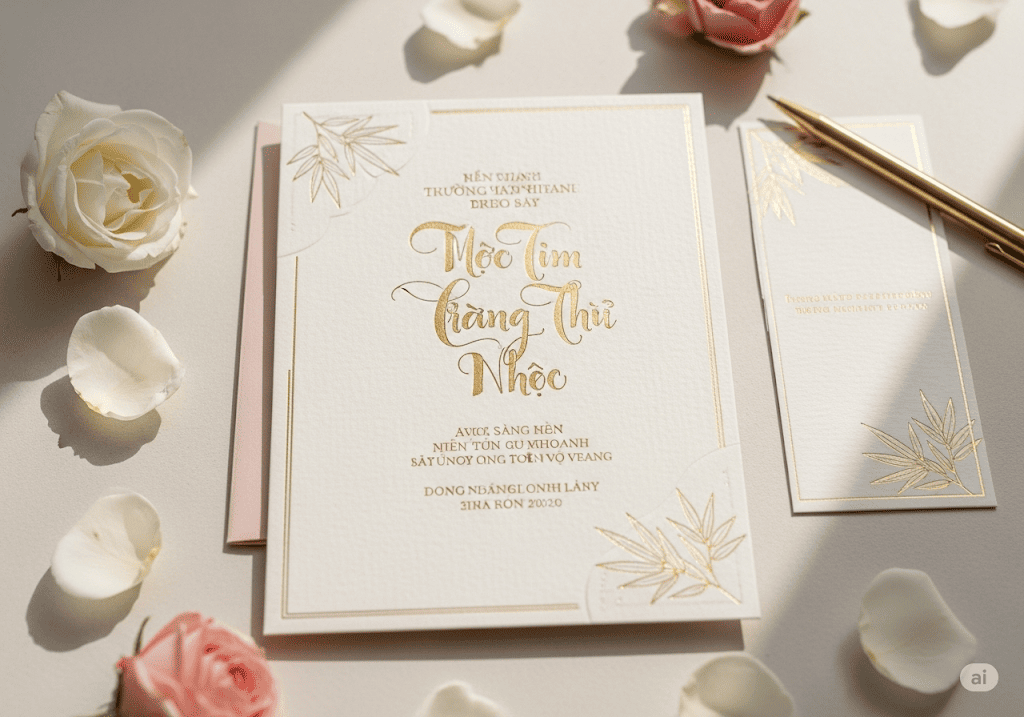
Tìm kiếm một font chữ thư pháp việt hóa vừa đẹp vừa không lỗi hiển thị có thể khiến bạn mất khá nhiều thời gian. Để giúp bạn, chúng tôi đã tuyển chọn và kiểm tra kỹ lưỡng danh sách hơn 20 bộ font miễn phí, sẵn sàng để bạn tải về và thổi hồn văn hóa Việt vào các thiết kế của mình.
Chắc hẳn bạn đã từng khó chịu khi tải về một font thư pháp ấn tượng, nhưng khi gõ tiếng Việt lại bị vỡ ký tự ‘đ’, ‘ă’ hay mất dấu thanh. Đây là vấn đề phổ biến nhất, làm ảnh hưởng trực tiếp đến chất lượng của các ấn phẩm quan trọng như thiệp chúc Tết, bìa sách hay bao bì sản phẩm.
Bài viết này không chỉ là một danh sách để tải về. Chúng tôi sẽ đi sâu vào cách nhận biết một font đã được Việt hóa chuẩn, hướng dẫn cài đặt nhanh chóng và chia sẻ các mẹo phối hợp chuyên nghiệp để tạo ra những tác phẩm thực sự có hồn và đẳng cấp.
Trước khi khám phá bộ sưu tập, hãy cùng tìm hiểu nền tảng cốt lõi: font thư pháp Việt hóa thực chất là gì và tại sao nó lại là yếu tố không thể thiếu trong thiết kế hiện đại.
Font chữ thư pháp Việt hóa là gì và tại sao lại được ưa chuộng?
Tại sao font chữ thư pháp Việt hóa lại quan trọng trong thiết kế?
Về cơ bản, font thư pháp là gì? Đây là một bộ ký tự số hóa mô phỏng nét bút lông uyển chuyển của nghệ thuật thư pháp truyền thống, nhưng đã được tinh chỉnh kỹ thuật để hiển thị đầy đủ và chính xác hệ thống dấu câu phức tạp của tiếng Việt. Việc “Việt hóa” này chính là yếu tố cốt lõi tạo nên giá trị sử dụng thực tế của chúng.
Sử dụng chữ thư pháp tiếng việt không chỉ là một lựa chọn thẩm mỹ, mà còn mang lại chiều sâu văn hóa và cảm xúc cho thiết kế. Ví dụ, một tấm thiệp chúc Tết, bìa sách về lịch sử, hay bao bì sản phẩm truyền thống sẽ ngay lập tức trở nên có hồn và trang trọng hơn. Đây là cách nhanh nhất để truyền tải giá trị cội nguồn trong bối cảnh typography việt nam hiện đại. Tuy nhiên, sai lầm phổ biến nhất mà nhiều người mới mắc phải là sử dụng các font chưa được Việt hóa hoàn chỉnh, dẫn đến lỗi hiển thị các ký tự như ‘đ’, ‘ă’, ‘ư’ hoặc các dấu thanh.
Để tránh lãng phí thời gian và đảm bảo chất lượng thiết kế, hãy luôn kiểm tra font trước khi sử dụng bằng quy trình đơn giản sau:
- Gõ một câu tiếng Việt đầy đủ dấu: “Mừng xuân sang, chúc vạn sự thành công tốt đẹp.”
- Nếu tất cả ký tự và dấu câu hiển thị mượt mà, không bị vỡ hay biến thành ô vuông, font đó đã sẵn sàng để sử dụng.
Hiểu rõ ý nghĩa font thư pháp và tầm quan trọng của việc Việt hóa sẽ giúp bạn lựa chọn công cụ phù hợp, tạo nền tảng vững chắc cho các tác phẩm của mình. Giờ thì hãy cùng khám phá danh sách các font đẹp nhất đã được chúng tôi tuyển chọn kỹ lưỡng ở phần tiếp theo.
Đâu là những font chữ thư pháp Việt hóa đẹp và miễn phí đáng tải nhất?
Để giúp bạn tiết kiệm thời gian tìm kiếm, chúng tôi đã tuyển chọn và tổng hợp danh sách hơn 20 bộ font chất lượng, sẵn sàng để bạn download font thư pháp việt hóa và sử dụng ngay. Các phông chữ này không chỉ đẹp về mặt thẩm mỹ mà còn được kiểm tra kỹ lưỡng, đảm bảo hỗ trợ đầy đủ ký tự tiếng Việt, phù hợp cho mọi mục đích từ thiết kế thiệp mời, ấn phẩm marketing đến các dự án cá nhân.
Font thư pháp nào phù hợp cho thiết kế trang trọng?
Đối với các ấn phẩm đòi hỏi sự trang trọng như thiệp cưới, câu đối Tết, hay bằng khen, các font thư pháp cổ điển là lựa chọn hoàn hảo. Một trong những cái tên nổi bật nhất là font ông đồ việt hóa, với những nét bút phóng khoáng, mô phỏng chân thực bút lông trên giấy dó. Bên cạnh đó, các font như VNI-Thufap hay UTM Thuphap cũng là những lựa chọn tuyệt vời, mang lại cảm giác trang nghiêm và hoài cổ cho thiết kế của bạn.
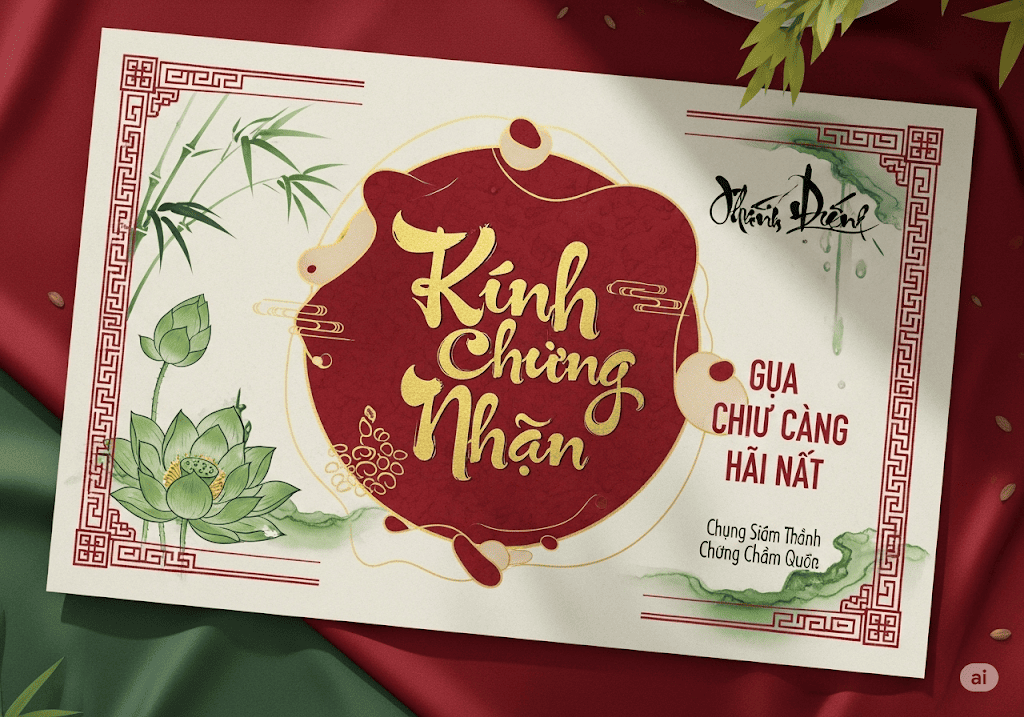
Đây là bước cực kỳ quan trọng nhưng thường bị bỏ qua. Trước khi sử dụng một font thư pháp đẹp cho các dự án thương mại (thiết kế bán hàng, logo, quảng cáo), hãy luôn kiểm tra file “license.txt” hoặc “readme.txt” đi kèm trong tệp tải về. Nếu không có ghi chú rõ ràng, mặc định font đó chỉ nên dùng cho mục đích cá nhân để tránh rủi ro pháp lý. Việc này không chỉ bảo vệ bạn mà còn thể hiện sự tôn trọng đối với công sức của tác giả.
Sau khi đã chọn được font ưng ý, việc cài font chữ cho máy tính là bước tiếp theo để đưa chúng vào sử dụng. Quá trình này rất đơn giản, chỉ cần thực hiện một lần là font sẽ tự động xuất hiện trên hầu hết các phần mềm hệ thống như Word, Excel và các công cụ thiết kế chuyên nghiệp. Dù bạn dùng Windows hay MacOS, các bước thực hiện đều nhanh chóng và trực quan.